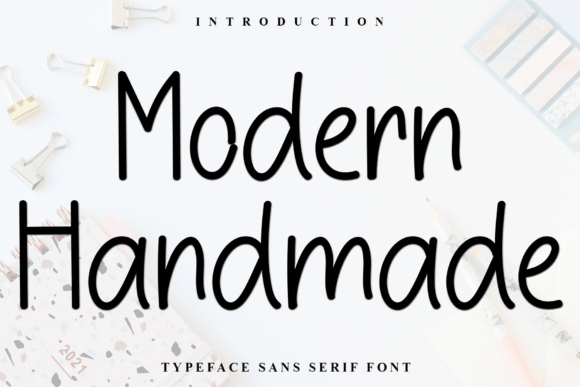
Modern Handmade
Modern Handmade – La police festive qui fait briller vos créations
À la recherche d’une typographie qui incarne l’esprit chaleureux des fêtes ? Modern Handmade est la réponse parfaite. Cette police décorative, à la fois joyeuse et pleine de charme, transforme instantanément cartes de vœux, étiquettes cadeaux et tout projet à thème hivernal en véritables pièces d’art. Son style manuscrit et ses ligatures uniques offrent une ambiance nostalgique tout en restant résolument moderne.
Pourquoi choisir Modern Handmade ?
- Design festif et ludique : Des éléments décoratifs subtils qui rappellent les guirlandes, les flocons et les boules de Noël, idéal pour capturer l’atmosphère des fêtes.
- Polyvalence créative : Parfaite pour les cartes de vœux, les invitations, les tags cadeaux, les affiches de Noël et les projets de branding saisonnier.
- Glyphes et ligatures complets : Grâce à son encodage PUA, vous avez accès à toutes les formes spéciales et aux ligatures sans effort, garantissant une mise en page fluide.
- Qualité professionnelle : Chaque caractère a été soigneusement dessiné pour assurer une lecture claire même à petite taille.
Conseils d’utilisation
- Associez Modern Handmade à une police sans‑serif neutre (ex. : Open Sans) pour un contraste élégant.
- Jouez avec les couleurs traditionnelles de Noël – rouge, vert, or – pour renforcer l’impact visuel.
- Utilisez les ligatures spéciales pour créer des mots‑clés décoratifs comme « Joyeux Noël » ou « Bonne année ».
- Intégrez des textures légères (papier froissé, effet neige) autour du texte pour un rendu encore plus magique.
Conclusion